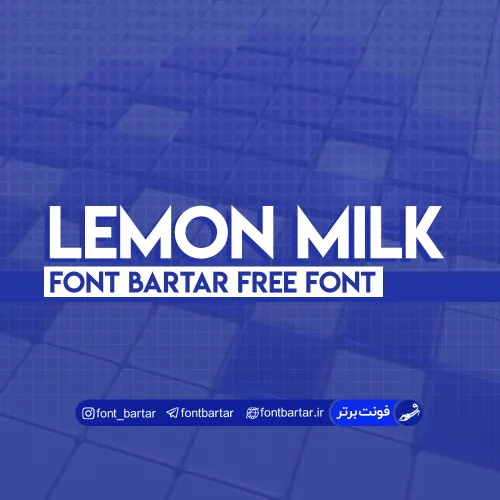
فونت انگلیسی Lemon Milk
فونت انگلیسی Lemon Milk ، فونت بسیار زیبا با ساختار منطقی ، فونت Lemon Milk یکی از فونت های پرطرفدار لاتین می باشد و نزدیک به 2.5 میلیون دانلود برای نسخه پیشین این فونت به ثبت رسیده است.فونت Lemon Milk یک تایپوفیس اپن سورس ازmarsnev است که به ادعا این کمپانی نرم افزاری در نسخه پیش رو حروف بزرگ و کوچک نسبت به نسخه پیشین همسان سازی شده است و به عبارتی دیگر این نسخه یکپارچه و منسجم تر است .فونت لِمون میلک یک فونت کلاسیک است که چینش حروف و نحوه قرار گیری خطوط فانتزی است و همین ویژگی یعنی ساختار کلی کلاسیک اما چینشی فانتزی ، زیبایی وصف ناپذیری تولید کرده.
فونت Lemon Milk مورد استفاده برای:
• طراحان وب سایت و گرافیست های خلاق می توانند از این مجموعه زیبا فونت در طراحی پروژه های تبلیغاتی و تجاری خود کمک بگیرند.